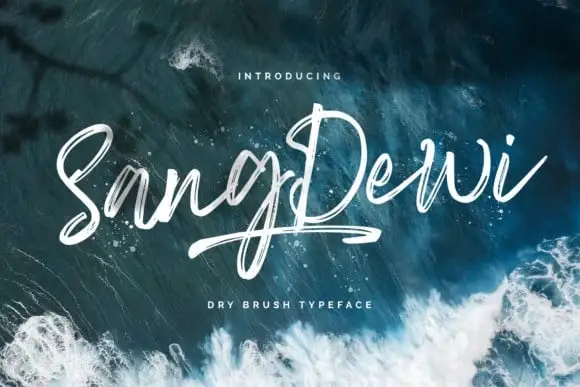
Sang Dewi Brush Font – Download Grátis
A Sang Dewi Brush Font é uma fonte script desenvolvida para quem valoriza a elegância e o encanto no design visual. Feita por um talentoso designer chamado StringLabs, essa fonte tem como inspiração as escritas manuscritas de forma elegante e fluida, criadas com a ajuda de uma caneta-pen. Esta fonte é perfeita para aplicar em uma variedade de projetos: desde materiais promocionais que exigem um tom autêntico e confiável até embalagens de produtos e identidades visuais. Suas linhas elegantes e suaves permitem que você explore sua criatividade ao criar designs variados, seja para promover sua marca ou expressar suas ideias de uma forma única e sofisticada. Experimente a Sang Dewi Brush Font em seu próximo projeto visual para adicionar uma pitada de estilo autêntico à sua produção.